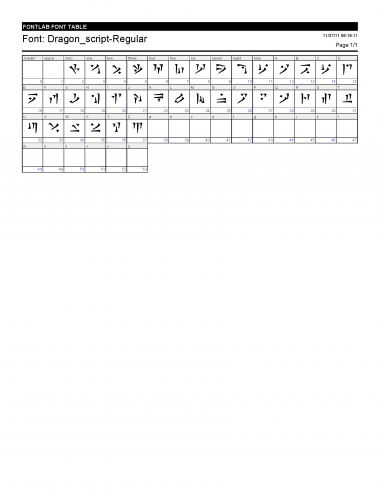
• Das sind die Buchstaben A-Z (ausgenommen C) Der Drachenschrift aus "The elder scrolls V -Skyrim" Ich wollte umbedingt einen Schriftsatz vür Word usw. da ich keinen gefunden habe, hab ich einfach jeden Buchstaben Pixel für Pixel von Bildern übertragen ^^ Ach ja! Ihr müst "noch" alles in Großbuchstaben schreiben... Das war die erste schrift die ich hir erstellt habe und ich hab es zu spät bemerkt. Werde ich noch ändern!!!
Übrigens hier habe ich eine Liste mit Buchstaben und Zahlen bzw Ziffern drauf von der Drachensprache.
Drachenschrift - Skyrim V1by N-Joke